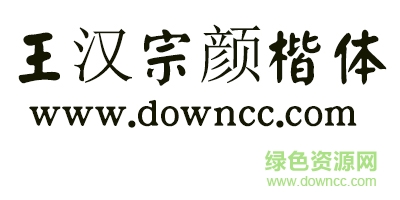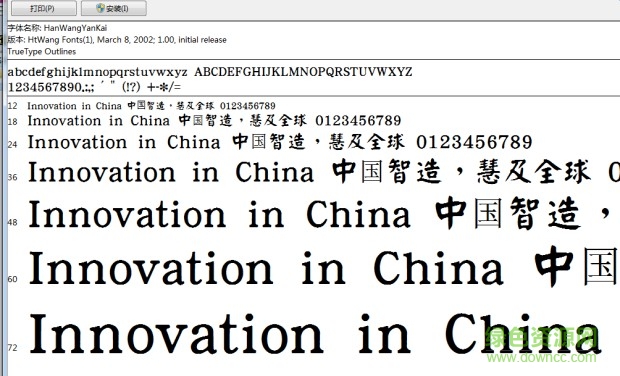
王漢宗顏楷體在多個行業(yè)都有使用!王漢宗顏楷字體兼具了楷體和顏體子的外形特點,無論是設計廣告還是進行商標設計都很不錯!歡迎用戶下載安裝使用。
王漢宗顏楷體字體是一款超具個性的字體,可以應用于海報設計、創(chuàng)意廣告、藝術設計、平面設計等應用!需要的用戶快來綠色資源網(wǎng)下載吧。